## 概念
一个好的界面设计,一定会有定义清晰的字体规范。
### Overline / eyebrow
An overline is a very short, relatively small piece of text that is placed over a header or a subheader. Before we continue with the explanation, here’s an example, since we know that the term “overline” isn’t very well known so you might have no idea what we’re talking about.
### 为什么要有字体规范?
字体比例是一个界面中使用的所有字体尺寸的集合。你可以把任何一个用户界面拿出来,收集其屏幕上使用的所有尺寸,然后你就会得到一个字体比例。也就是说,它应该在你的设计项目开始之前创建,所以我们不是从一个完整的界面中 "提取 "尺寸,而是用字体比例来创建它。
为什么呢?简而言之,它可以节省大量的时间,并使应用不同字体风格的过程更加精简和直接。如果你看到自己问 "我应该为这个标题使用 32 px 还是 34 px?",这意味着你需要掌握创建字体比例的艺术。继续阅读以了解更多。
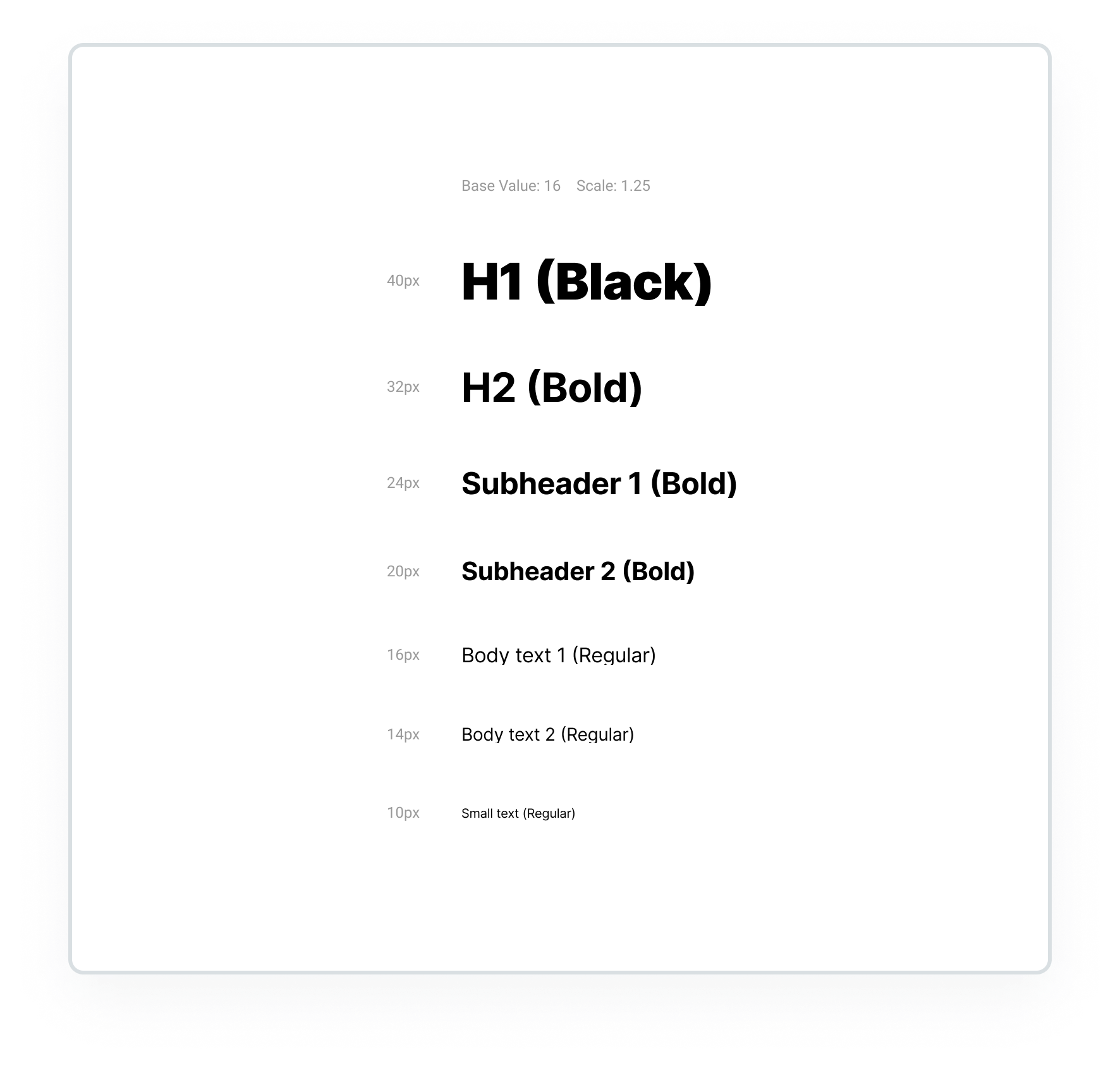
## 常见字体梯度
### Apple
- 参考 [Typography - Visual Design - macOS - Human Interface Guidelines](https://developer.apple.com/design/human-interface-guidelines/macos/visual-design/typography/)
- Large title
- Title 1
- Title 2
- Title 3
- Headline
- Body
- Callout
- Subheadline
- Footnote
- Caption1
- Caption2
从 2023 iOS 官方源文件记录的。
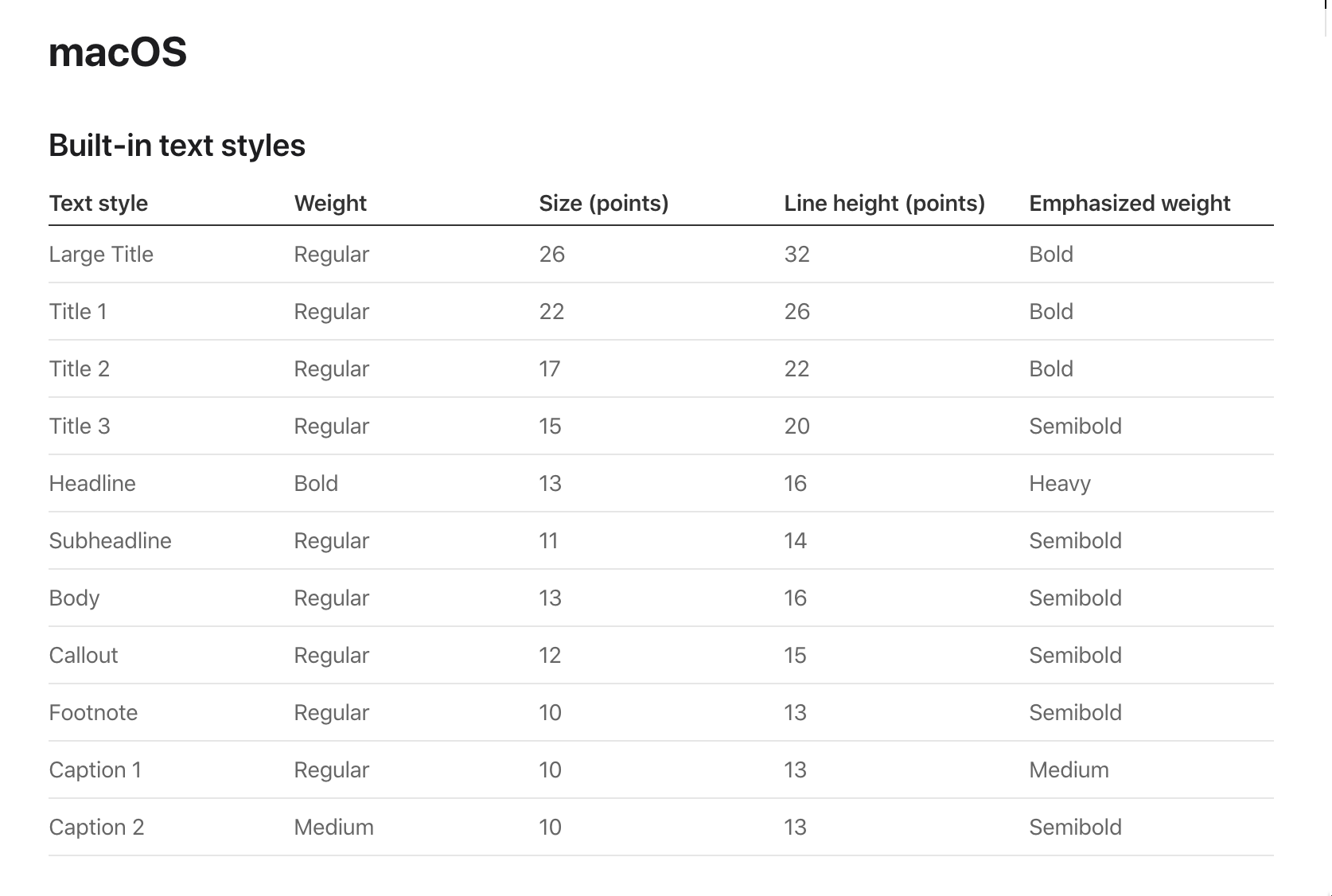
### Figma 官方
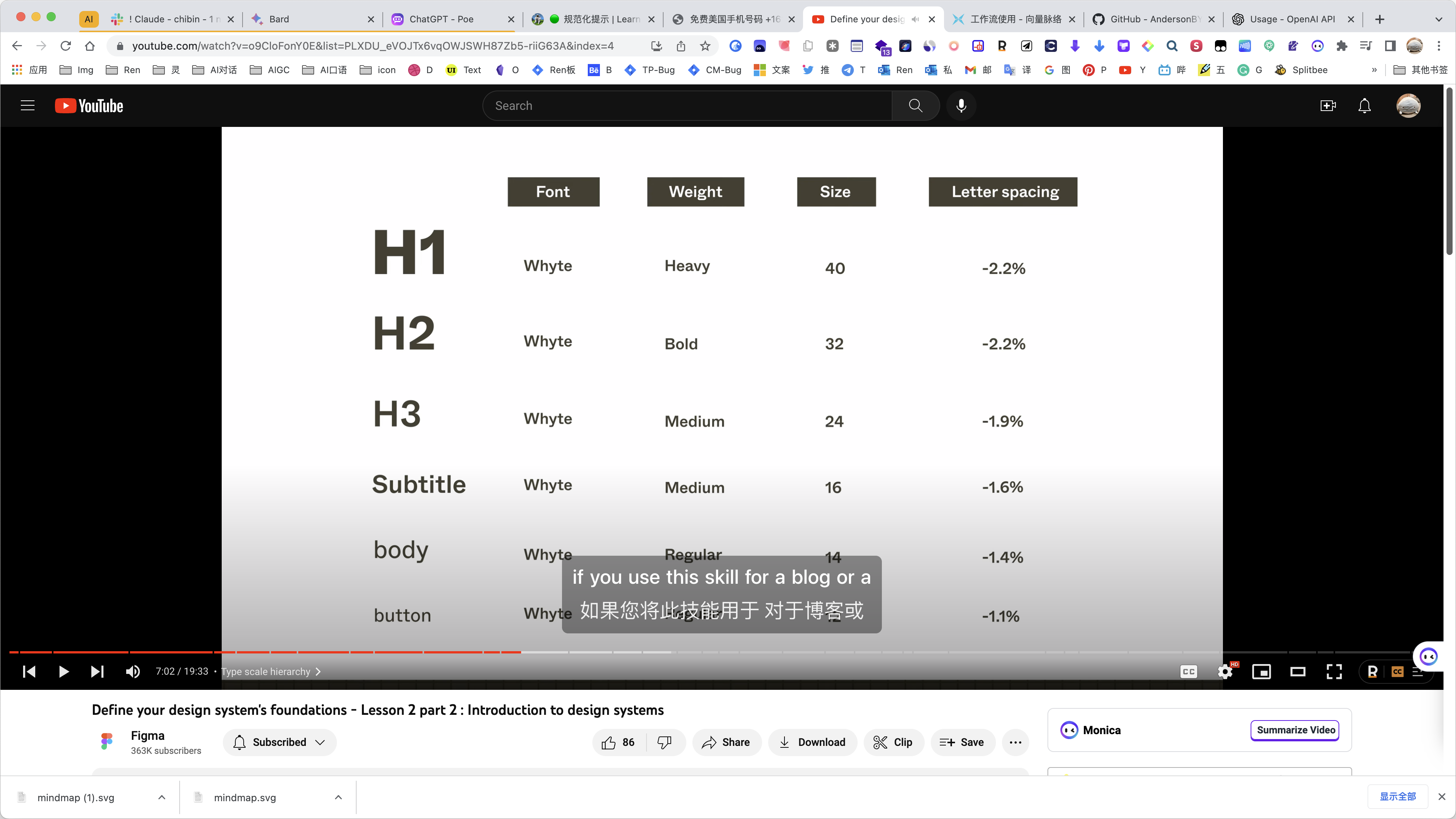
## 最佳实践
### DO
- 优先用字重构建视觉层级? Use font weights to establish hierarchy
- 左边的例子不一定是 “错误的”。用户将首先阅读标题,然后阅读正文,就像我们想要的那样。然而,我们可以做同样的事情,**使用更高的权重(如粗体或半粗体)在屏幕上占用更少的空间。** 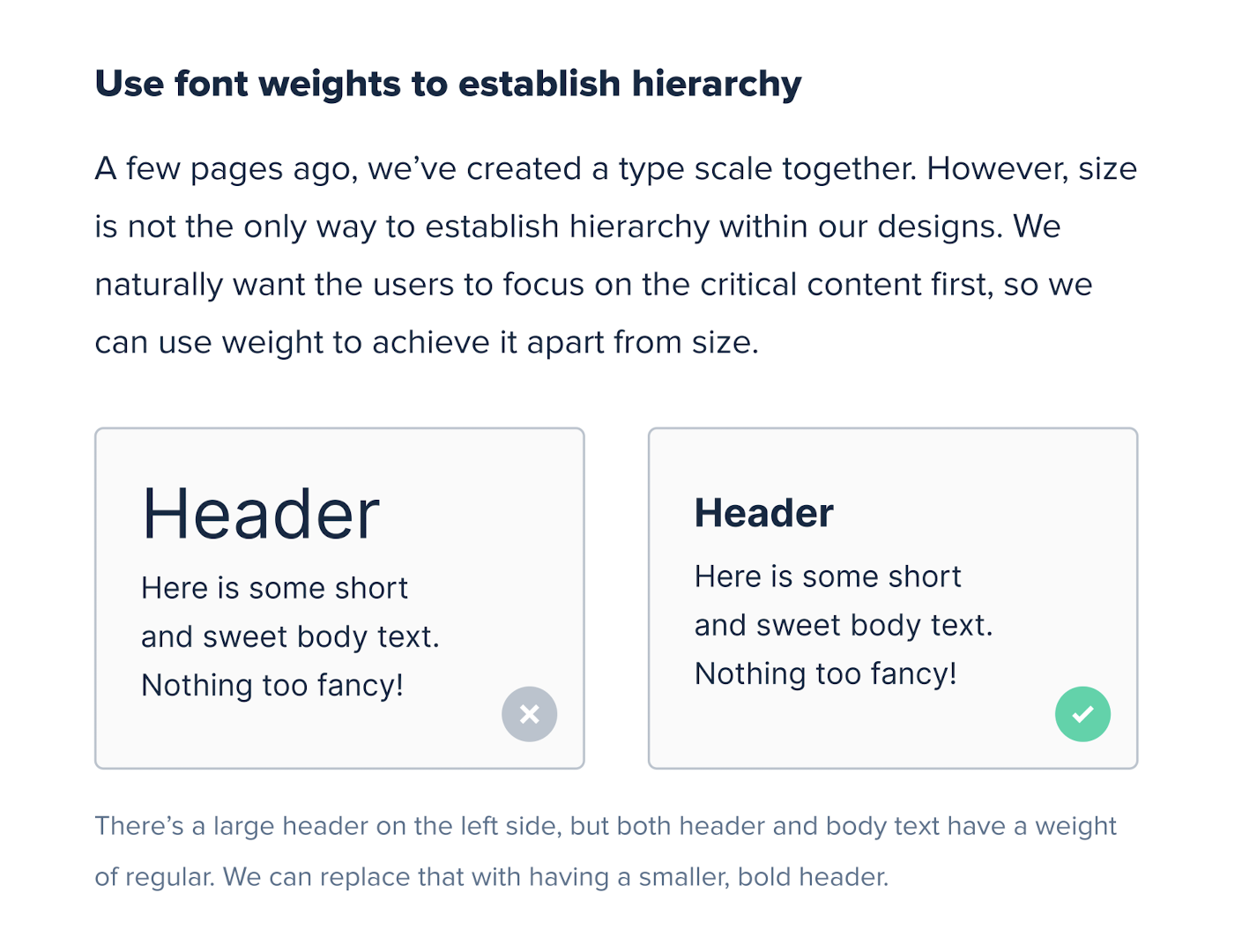
- Align different text sizes to the baseline
- 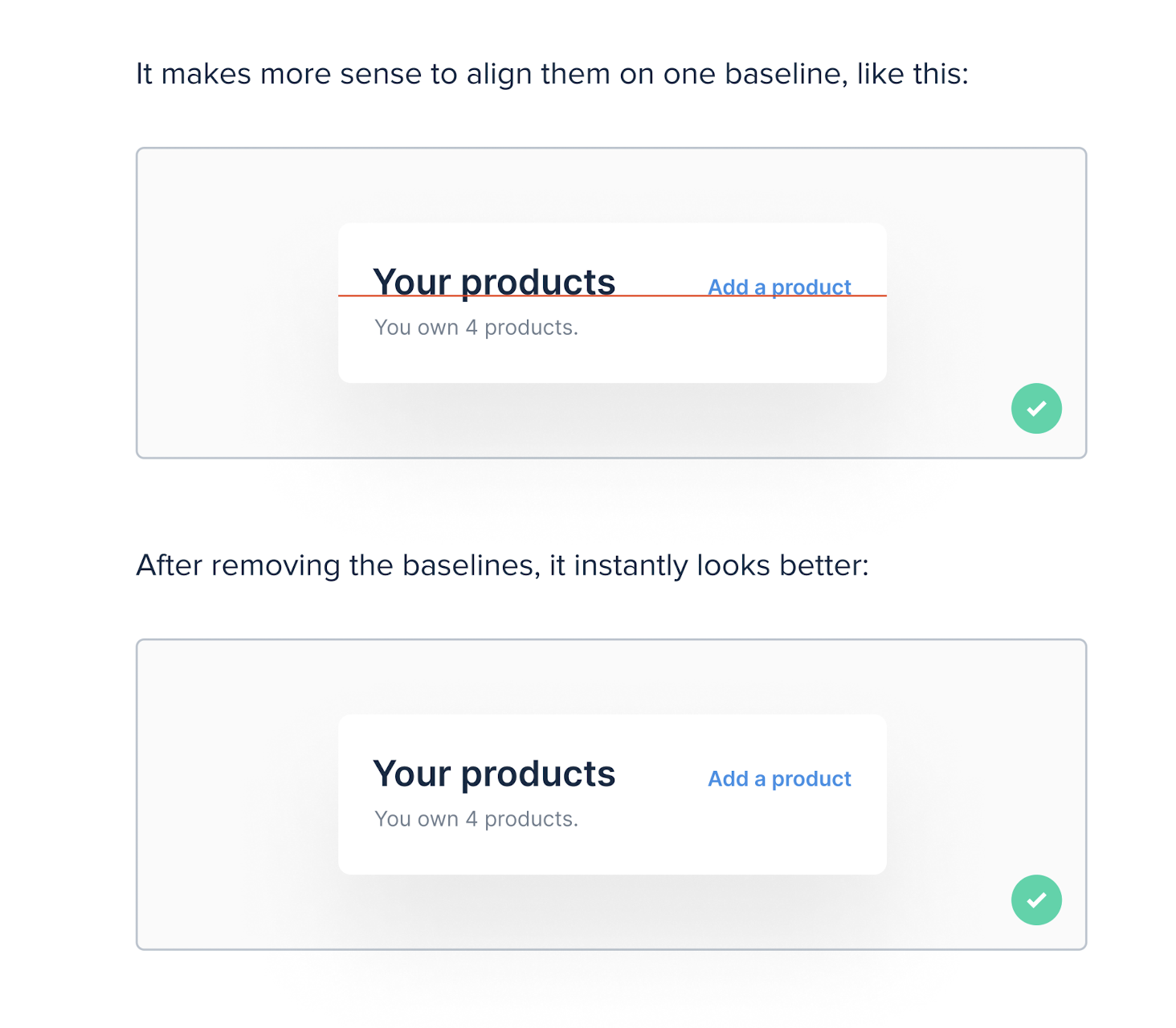
- Avoid Rags
- 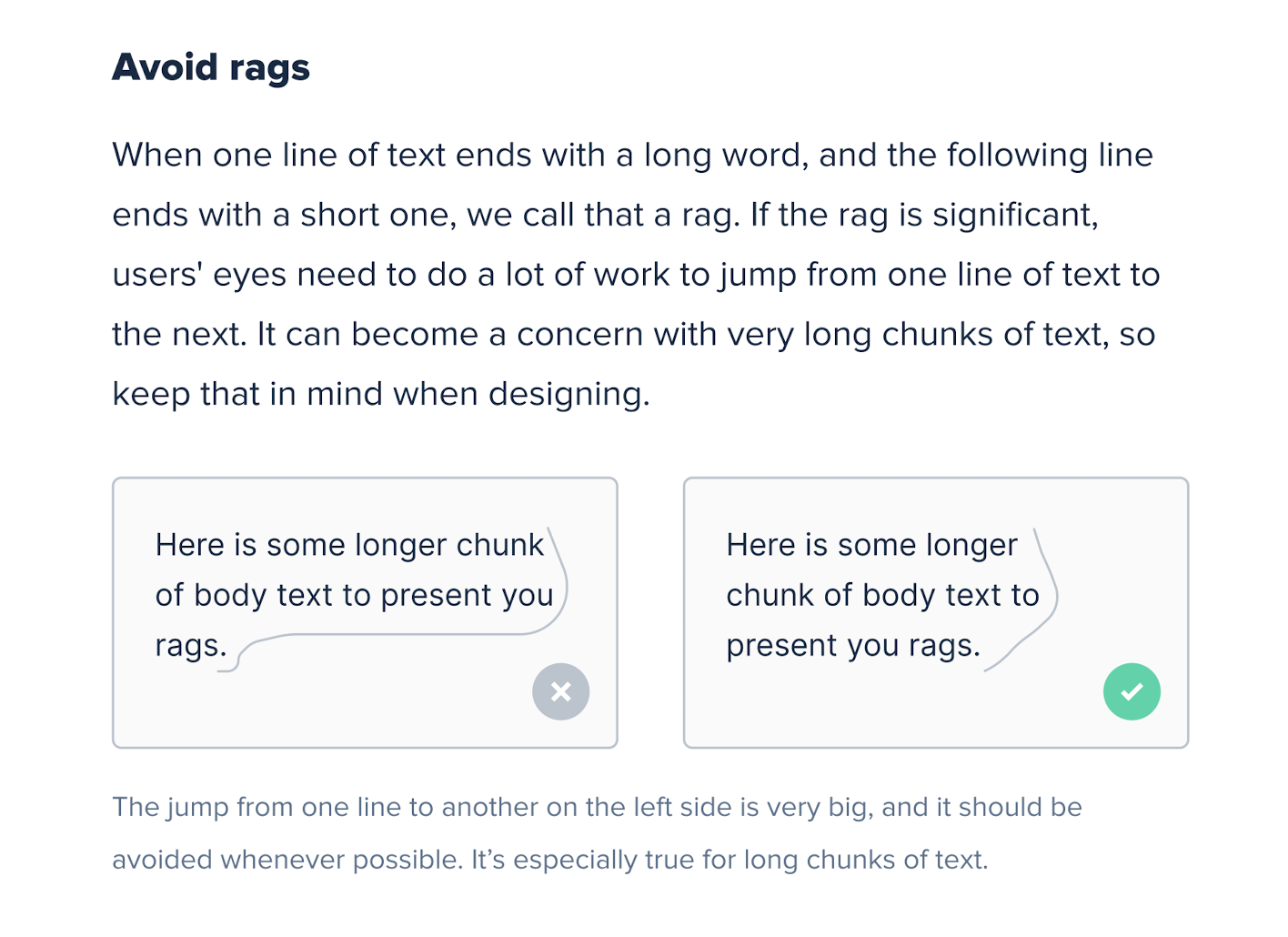
- 西文排版时, **The optimal line length** for your body text is considered to be 50 to 60 characters in a line. Using less or more can impact readability. 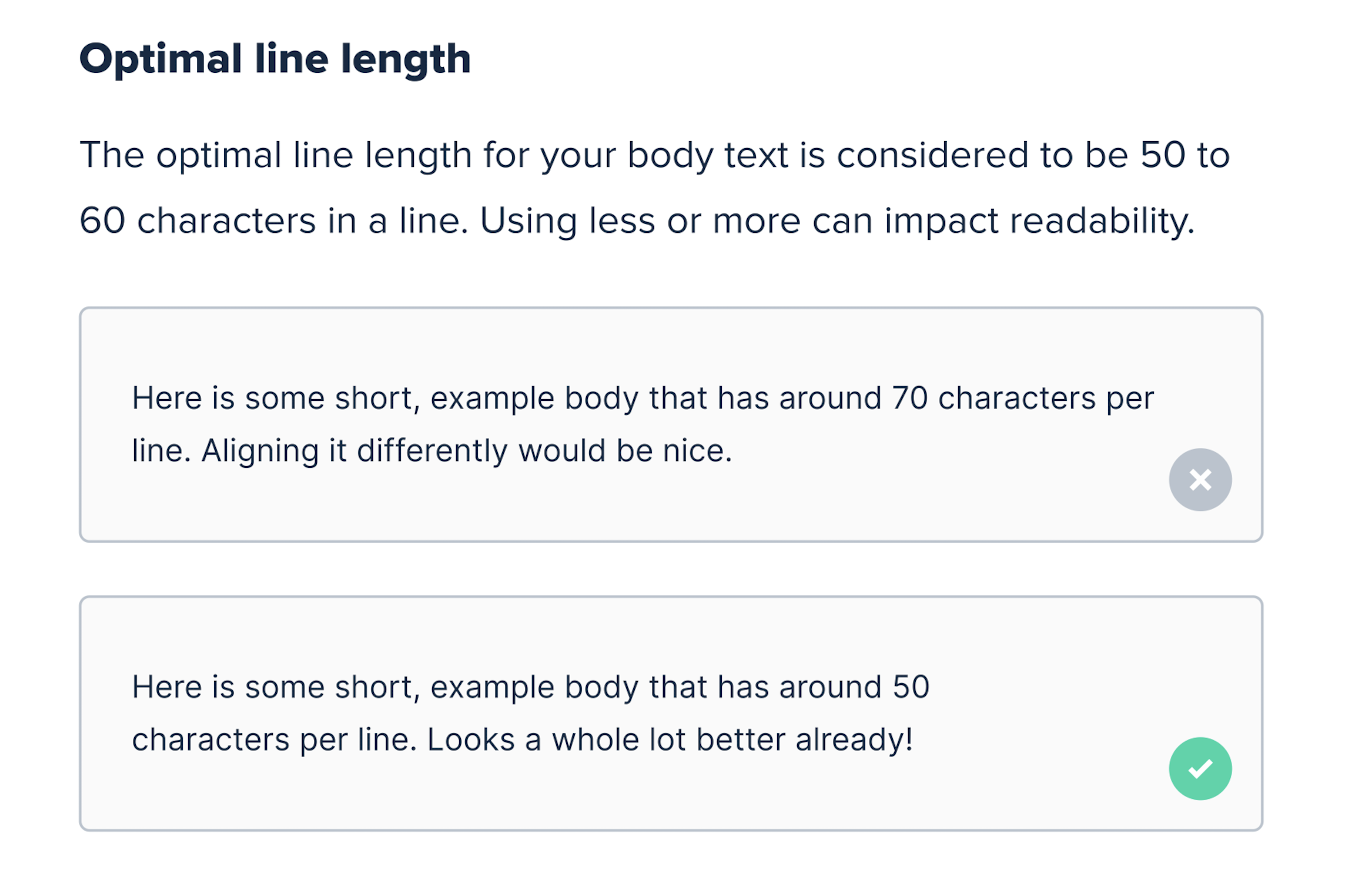
- 标题,When to change **letter spacing?**
- 如果标题文字过大,可以适当调小 Letterr spacing。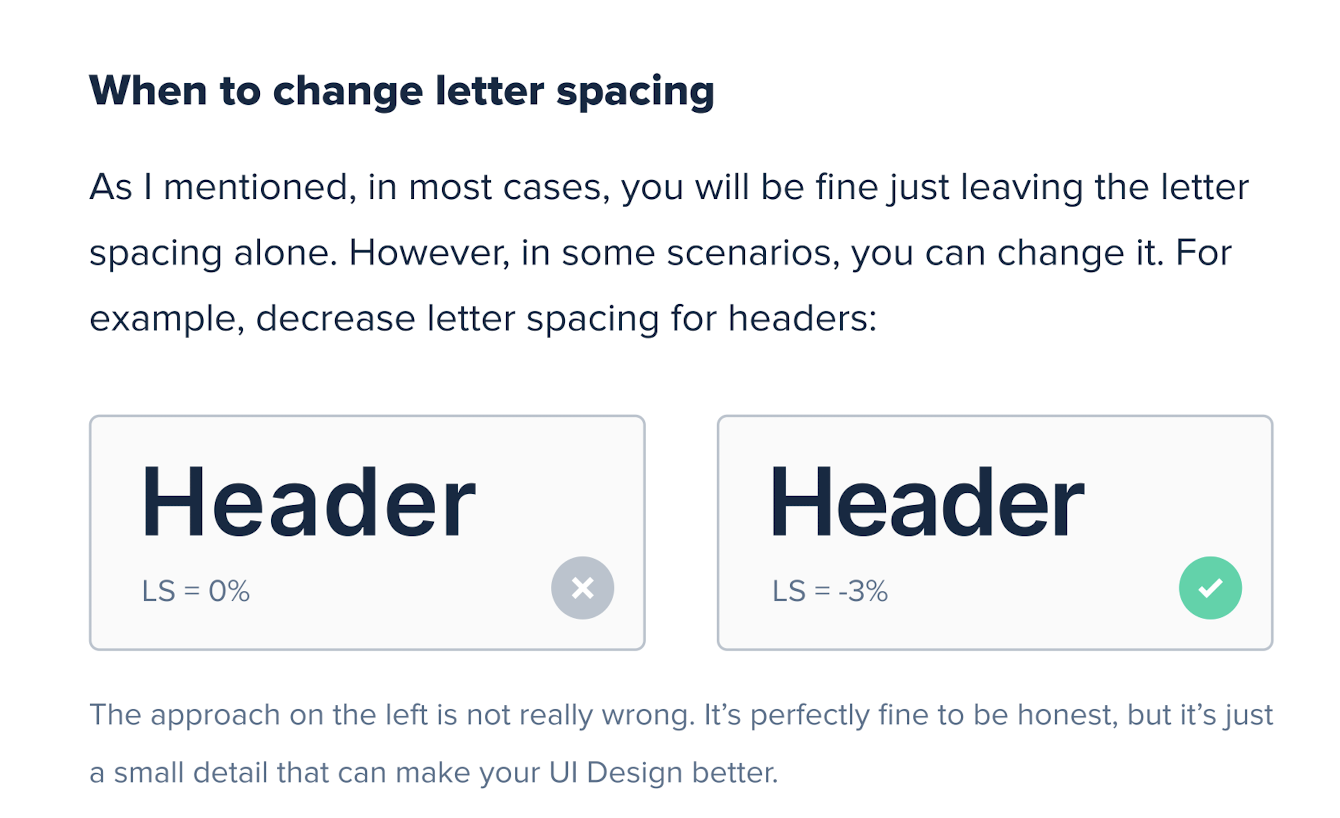
- 一般情况下,标题的行高会比正文的行高要小。例如正文是 1.5 倍,标题是 1.25~1.3 倍。
- 在 CLoudspace 这个设计系统里也有相关的设计支持。 < [https://cloudscape.design/foundation/visual-foundation/typography/#type-styles>](https://cloudscape.design/foundation/visual-foundation/typography/#type-styles>)
- 在一些国外的设计教材中,也有相关案例。
- 字号大小一定要克制,大部分页面 2 – 3 种基本就够了。
- 例如 12、14、16,能应付大多数 B 端产品了。
- **如何利用工具创建更好的 Scale 比例?**
- 用 #Figma插件 Typescales
- 还有 Textyles (不是很实用的样子)
### Don't
- 字重不要太轻,很难阅读。
- [Vol 7 应用市场规则大更新、UI基础第一篇-字体系统 (hsxg.ghost.io)](https://hsxg.ghost.io/vol7/) 这篇文章描述了,如何优化一个旧的设计,重新梳理字号,间距,减少零乱的字体效果,提升设计效率与开发效率。
- [细数 Pingfang SC 的七宗罪 · 李瑞东 LRD.IM](https://lrd.im/blog/2022-01-17-8a5738fc2340.html) 感觉写的有点水平。